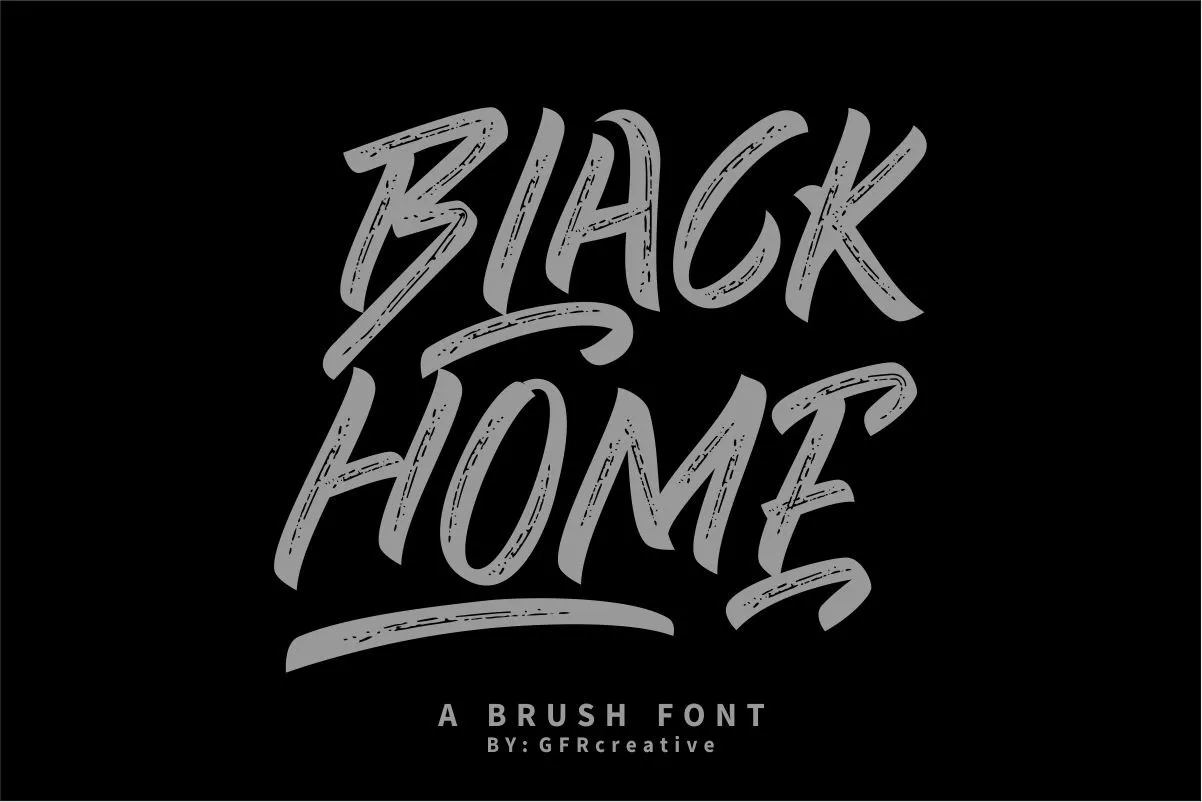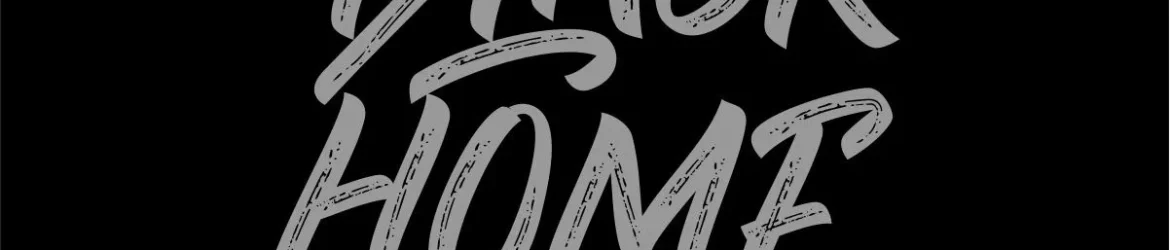
A BLACK HOME Font é uma elegante escolha para quem busca adicionar um toque autêntico aos seus projetos digitais. Sintetizada com estilo de caneta, essa fonte do GFR Creative apresenta textura forte e grosso que dão vida à cada design criativo. Suas linhas robustas e rústicas destacam-se em qualquer layout, tornando-a perfeita para aplicação em logotipos, marcações, fotografias, convites de casamento, produtos, embalagens, eventos especiais ou qualquer outro trabalho que necessite de conteúdo escrito à mão. Combinar essa fonte com as cores e formas únicas do BLACK HOME permite criar designs memoráveis que transmitam um senso de qualidade e profissionalismo, tornando-a uma excelente opção para quem busca incorporar elementos artesanais em seu design digital.